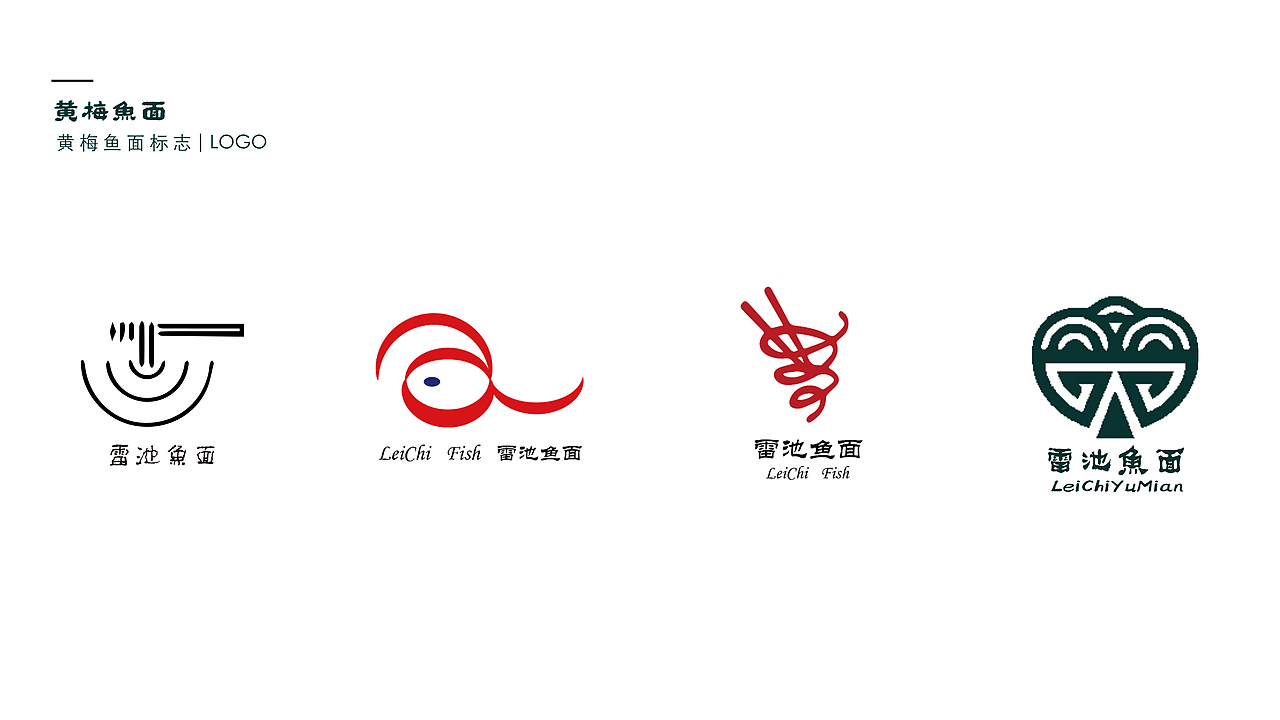
乡村振兴·黄梅鱼面品牌设计
对黄梅鱼面的现状进行调研分析,从乡村振兴的角度研究黄梅鱼面品牌的构建与应用,探索黄梅鱼面品牌设计的思路和方向,最终实现消费者对黄梅鱼面品牌的深度购买和体验。结合乡村振兴理念,对鱼面品牌进行调研,总结黄梅鱼面品牌存在的问题,从中寻找设计机会。基于乡村振兴理念设计黄梅鱼面品牌是一条创新、可行的路径。它不仅有利于黄梅鱼面品牌的推广与传播,而且给相关农产品品牌的设计提供设计思路和实践案例。
黄梅县地处湖北省,当地楚文化盛行,故选用楚文化中的食器--鼎作为logo设计的元素;龙感湖,又称雷池,盛产草鱼和青鱼,是黄梅鱼面的主要原料产地,故用此名。
根据前期调研和品牌调性以及提炼出来的关键词选定四种logo。第一个logo下半部分由鱼面的形状抽象演化而来;因“雷池”地处湖北龙感湖,楚文化盛行,故第二个logo字体-选用隶书,因其楚文化中崇尚红色,故配色为红色,图形以鱼的形状变形而来,中间的蓝色既是鱼的眼睛,又是“雷池”的蓝。第三个图形用筷子和鱼面的形状进行结合,而鱼面缠绕的形状,又可以理解为深不见底的雷池。第四个logo整个图形分上下两部分上部分为鱼面的形状简化而来,下部分为楚文化中的食器变化而来。
相传,黄梅县有一因渔业变富的富人,有湖区亲戚来访,送以鱼,富人唯恐鱼腐,遂将鱼去皮、去骨、用石磨配以苕粉捣成泥,擀成面状、蒸熟、晒干、切丝而成面条状,至此黄梅渔民争相传颂。从此历史中可得出:(1)鱼面制作工艺复杂,故黄梅当地人勤劳、精致、热爱生活,这 直接导致鱼面的产生;(2)黄梅人心思缜密,导致鱼面做工精良;(3)黄梅当地重礼节,注重送礼礼节,礼盒装鱼面是重点。从送礼(鱼)中产生鱼面包装定位,赋予鱼面“礼节属性”,故鱼面礼盒包装是此包装设计重点。
黄梅鱼面已经被国家列入为非物质文化遗产,它作为黄梅当地的一种传统小吃,代表了当地的民风民俗和当地的人文精神和特色文化,就宛如是黄梅的一张实物名 片,让人能更好的认识黄梅,了解黄梅。黄梅是一个小县城,有很多家庭并不是很富裕,进行黄梅鱼面品牌设计也可以对当地的经济带来收入,通过对包装升级也能提高个人的经济水平,从而达到乡村振兴的目的。黄梅鱼面作为非物质文化遗产,融入当地文化元素,彰显品牌内涵。文化是源远流长的,它是品牌永远的生命力,将本地文化融入品牌,并得以在终端展示,这是展现品牌内涵,提高品牌美誉度的最好方法。所以,将文化元素体现在黄梅鱼面的品牌设计上,产品也便有了厚重的文化底蕴,这种产品也更能经得起时间的推敲。